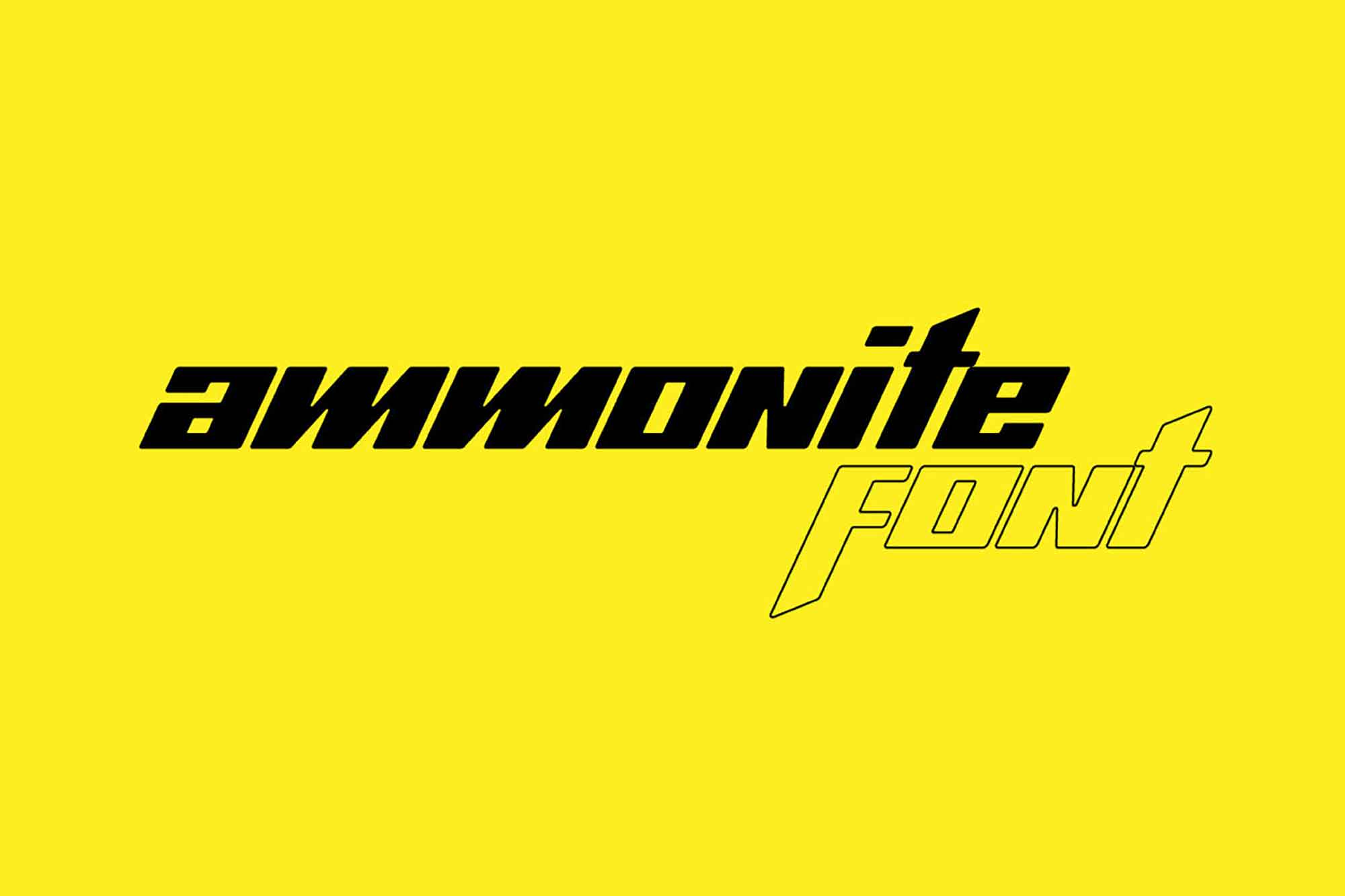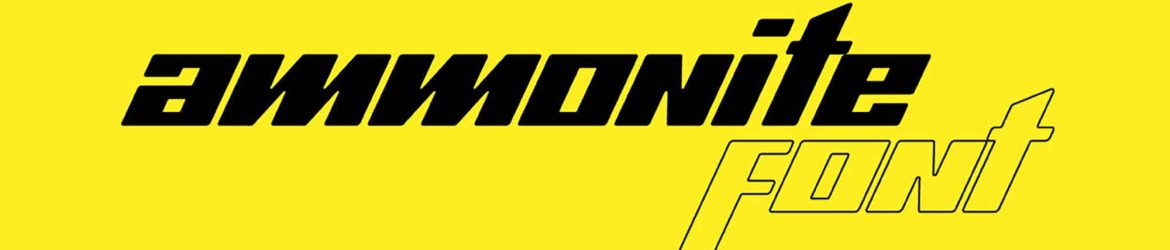
Ammonite Display Font – Download Grátis
A fonte Ammonite é uma opção perfeita para criar designs inspiradores e motivadores, especialmente para projetos que buscam despertar a energia dormida. Seja um lema inspirador, uma imagem emocionante ou uma decoração de flyer, esta fonte pode ajudar a transformar qualquer projeto em uma fonte de motivação. Ela é ideal para quem busca criar atmosferas energizantes e desafiadoras, especialmente para pessoas que estão em um impasse ou precisam de um impulso para começar a trabalhar. Seja para projetos de marca, logotipos, ou qualquer outro tipo de design, a fonte Ammonite é uma escolha excelente para criar um impacto imediato e motivador.